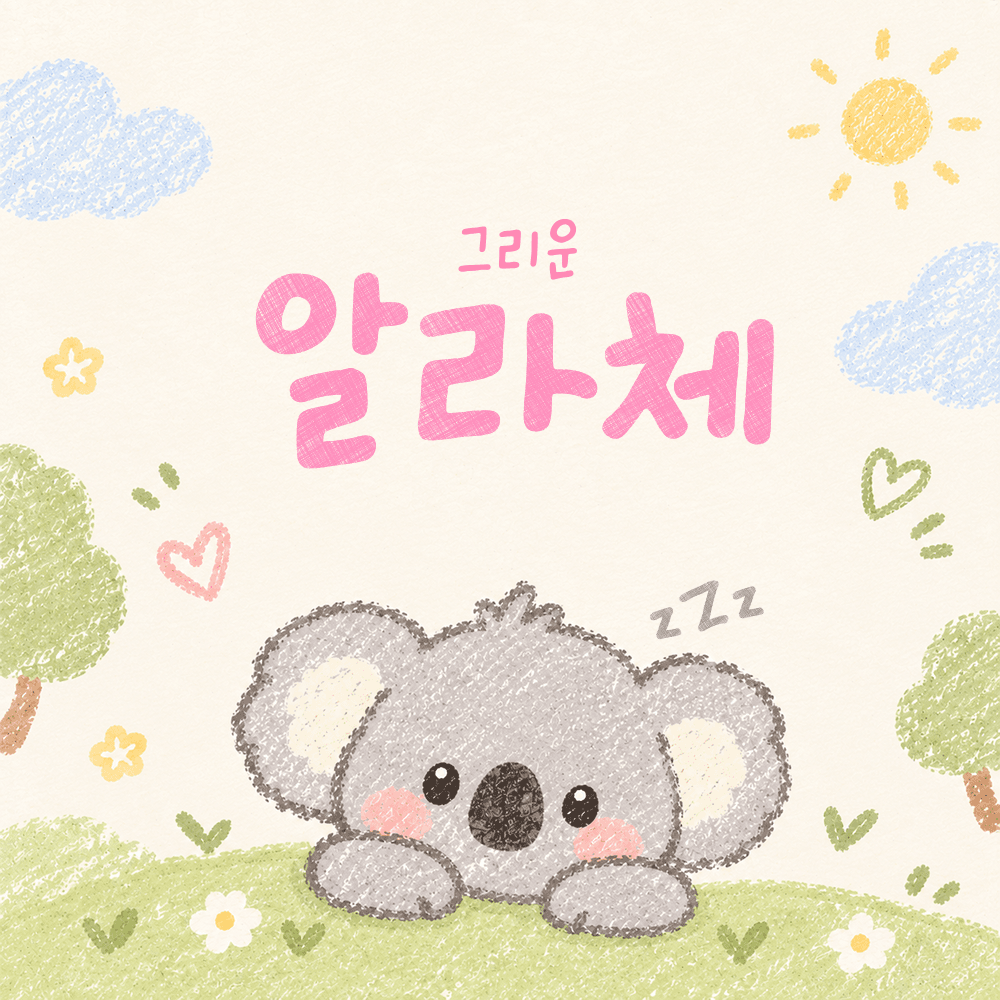
그리운 알라
Griun Alla Hyuna
그리운 알라 소개
코알라라는 별명과 제 이름을 담아 세상에서 하나뿐인 글씨체를 만들어보고 싶어서 제작했습니다. 반듯하기보다는 조금 삐뚤고 완벽하기보다는 손글씨만의 따뜻함을 담았습니다 보는 사람에게 작은 미소와 포근함을 전하는 글씨입니다♥